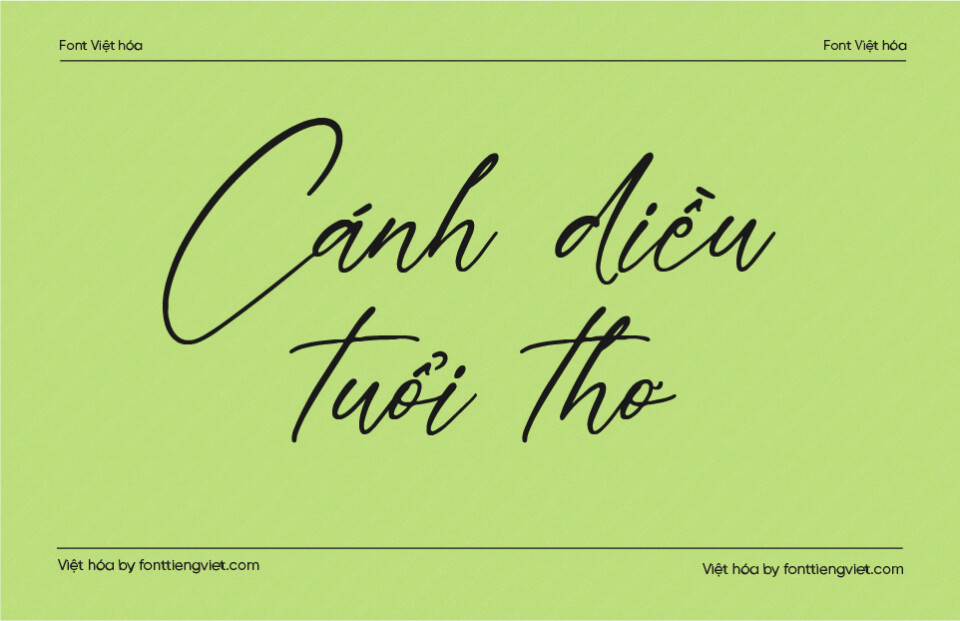
Trong thế giới thiết kế đồ họa và sáng tạo nội dung, việc lựa chọn một Font Chữ phù hợp có thể tạo nên sự khác biệt đáng kể. Đặc biệt, với những yêu cầu về tính thẩm mỹ và khả năng hiển thị tiếng Việt, các font Việt hóa luôn là lựa chọn hàng đầu. Hôm nay, chúng ta sẽ cùng khám phá một cái tên đang gây sốt trong cộng đồng thiết kế: Font Việt hóa 1FTV VIP Coldwell Bridges. Đây không chỉ là một phông chữ đẹp mắt mà còn là một công cụ mạnh mẽ, giúp nâng tầm mọi dự án của bạn, từ các bài tập học đường cho đến những ấn phẩm chuyên nghiệp.
Font Việt hóa 1FTV VIP Coldwell Bridges: Tuyệt tác của sự Sáng tạo và Tinh tế
Font Việt hóa 1FTV VIP Coldwell Bridges nổi bật với phong cách độc đáo, kết hợp giữa nét cổ điển và hiện đại, mang lại cảm giác sang trọng nhưng không kém phần năng động. Điểm mạnh lớn nhất của font này chính là khả năng Việt hóa hoàn chỉnh, đảm bảo mọi ký tự tiếng Việt, dấu câu và các ký tự đặc biệt đều được hiển thị một cách mượt mà và chính xác. Điều này cực kỳ quan trọng đối với học sinh, sinh viên khi tạo các bài thuyết trình, báo cáo hay các tài liệu học tập, giúp thông điệp được truyền tải rõ ràng và chuyên nghiệp.
Font Coldwell Bridges không chỉ dừng lại ở tính năng Việt hóa. Nó còn được chăm chút tỉ mỉ từng chi tiết, từ độ dày nét chữ đến khoảng cách giữa các ký tự, tất cả đều được tối ưu hóa để mang lại trải nghiệm đọc tốt nhất. Dù bạn sử dụng font này cho tiêu đề, đoạn văn bản dài hay các thiết kế đồ họa phức tạp, nó vẫn giữ được vẻ đẹp và tính dễ đọc tuyệt vời.
Tại sao Font Việt hóa Coldwell Bridges lại được Ưa chuộng trong Môi trường Giáo dục và Thiết kế?
Đối với học sinh, sinh viên, việc trình bày bài làm một cách chuyên nghiệp là vô cùng cần thiết. Một font chữ đẹp, dễ đọc như Font Việt hóa 1FTV VIP Coldwell Bridges có thể giúp bài thuyết trình hoặc luận văn của bạn gây ấn tượng mạnh mẽ hơn. Thay vì sử dụng các font mặc định đã quá quen thuộc, việc đổi mới bằng một phông chữ có cá tính sẽ thể hiện sự đầu tư và sáng tạo của người thực hiện.
Các giáo viên, giảng viên cũng có thể tận dụng font này để tạo ra các tài liệu giảng dạy, đề thi tốt nghiệp trung học phổ thông hoặc các bài kiểm tra chất lượng cao. Với khả năng hiển thị rõ ràng và phong cách chuyên nghiệp, font Coldwell Bridges giúp các tài liệu này trở nên hấp dẫn và dễ tiếp cận hơn cho người học. Đây là một yếu tố nhỏ nhưng có thể ảnh hưởng lớn đến hiệu quả học tập và giảng dạy.
Trong lĩnh vực thiết kế đồ họa, Font Việt hóa 1FTV VIP Coldwell Bridges mở ra không gian sáng tạo không giới hạn. Từ thiết kế logo, banner, poster cho đến các ấn phẩm tạp chí hay website, font này đều có thể đáp ứng một cách xuất sắc. Sự linh hoạt trong ứng dụng của nó cho phép các nhà thiết kế tự do thể hiện ý tưởng, mang lại những tác phẩm có giá trị nghệ thuật cao và gây ấn tượng mạnh với người xem.
Ứng dụng đa dạng của Font 1FTV VIP Coldwell Bridges cho Mọi Đối tượng
Không chỉ giới hạn trong phạm vi học đường hay thiết kế chuyên nghiệp, Font Việt hóa 1FTV VIP Coldwell Bridges còn có thể được ứng dụng rộng rãi trong nhiều lĩnh vực khác. Các blogger, vlogger có thể sử dụng font này cho hình ảnh đại diện, tiêu đề video hoặc các trích dẫn trên mạng xã hội để tạo phong cách riêng biệt. Các doanh nghiệp nhỏ cũng có thể tận dụng font này cho các ấn phẩm truyền thông, tạo dựng hình ảnh thương hiệu độc đáo và chuyên nghiệp.
Hơn nữa, tính “VIP” trong tên gọi của font này phần nào khẳng định chất lượng vượt trội và sự độc quyền mà nó mang lại. Đây không chỉ là một phông chữ miễn phí thông thường mà là một tài sản giá trị cho bất kỳ ai muốn nâng cao chất lượng sản phẩm hình ảnh và văn bản của mình. Sự đầu tư vào một font chất lượng như Coldwell Bridges chắc chắn sẽ mang lại những lợi ích đáng kể trong dài hạn.
Tóm lại, Font Việt hóa 1FTV VIP Coldwell Bridges là một lựa chọn tuyệt vời cho bất kỳ ai đang tìm kiếm một Font Chữ vừa đẹp mắt, vừa chuyên nghiệp lại vừa hỗ trợ tiếng Việt hoàn hảo. Dù bạn là học sinh đang chuẩn bị cho các kỳ thi quan trọng, một sinh viên đang hoàn thành đồ án tốt nghiệp, hay một nhà thiết kế đồ họa chuyên nghiệp, phông chữ này đều có thể đáp ứng mọi nhu cầu của bạn. Hãy trải nghiệm và cảm nhận sự khác biệt mà Font Việt hóa 1FTV VIP Coldwell Bridges mang lại cho các dự án của bạn!